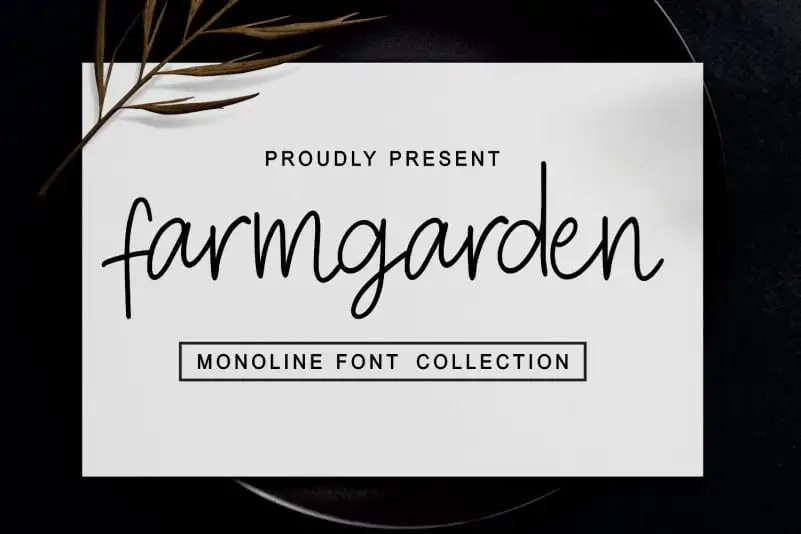
Farmgarden Handwritten Font – Download Grátis
A Farmgarden Handwritten Font é uma seleção de letras escritas à mão que traz um toque de delicadeza e simplicidade. Suas linhas curvas delicadas e sua natureza única tornam a letra perfeitamente adequada para diversas criações gráficas, desde cartazes até pequenos detalhes em design editorial. Composta por uma variedade de formas suaves e texturas distintivas, essa fonte permite que você dê vida às suas ideias criativas sem limitações. Seja para um projeto personalizado ou para dar um toque único a qualquer arte digital ou impressa, a Farmgarden Handwritten Font está aqui para transformar seus projetos. Navegue sua imaginação livremente e colecionue esta fonte de letras escritas à mão única com o Designer Mozarella.